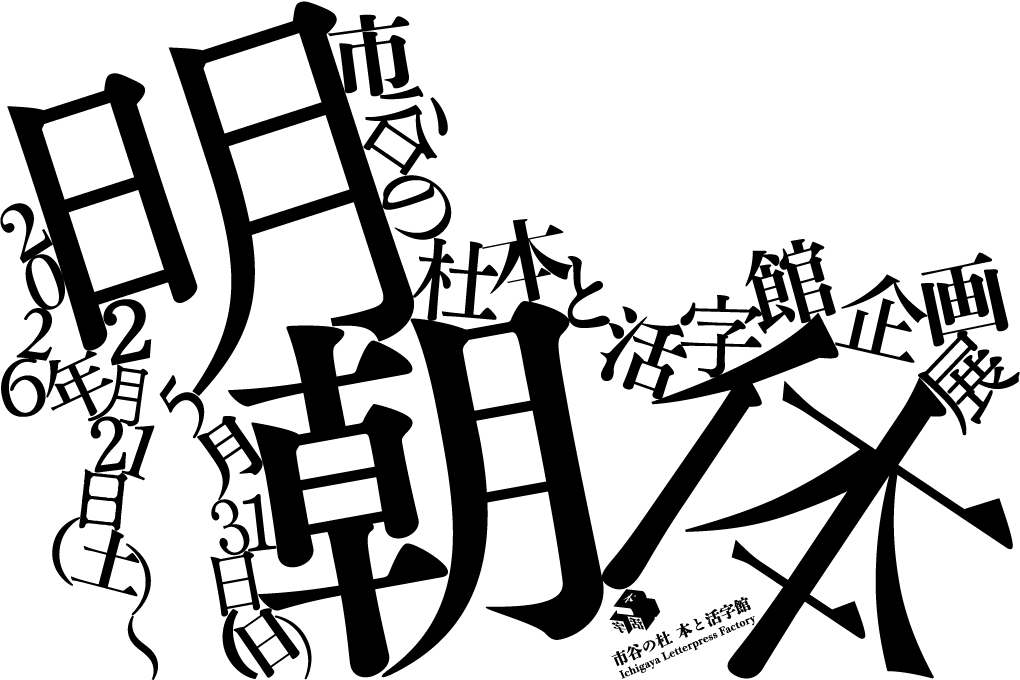
Monotype、企画展「明朝体」への資料提供に関するお知らせ
DNP主催「明朝体」展にMonotype®が協力――歴史ある多様な明朝体が一堂に、書体文化の魅力を発信
米国 Monotype Imaging Inc.の日本法人である Monotype株式会社(本社:東京都港区、以下 Monotype)は、大日本印刷株式会社(本社:東京都新宿区、以下 DNP)が運営する文化施設「市谷の杜(いちがやのもり)本と活字館」(東京都新宿区)にて開催される企画展「明朝体」へ、ライブラリフォントの筑紫書体シリーズをはじめとする明朝体資料を提供いたしました。
本企画展は、書体のスタンダードのひとつとして日本文化を支え続けてきた明朝体に焦点を当て、1世紀半以上にわたる明朝体の歴史を時代をさかのぼりながら紹介いたします。Monotypeは、本企画の趣旨に賛同し、書体デザインディレクター 藤田重信が生み出した、当社の日本語ライブラリフォントを代表する明朝体「筑紫明朝」の開発当初の資料等を提供し、展示に協力いたします。これを通じて、文字文化の魅力発信とフォント業界のさらなる発展に貢献してまいります。
筑紫書体とは
Monotype 書体デザインディレクター 藤田重信が2004年に生み出した「筑紫明朝」から始まった書体シリーズです。
金属活字の滲みを再現しながら新しさを取り入れ、画一的ではなく、文字本来の形をいかした字形デザインが特長です。懐かしさやあたたかみを感じさせ、見る人に郷愁を呼び起こします。一文字ごとの美しさはもちろん、文字組みした際の調和や文字同士が呼吸するような美しさも魅力です。明朝体、ゴシック体など、現在全15シリーズを展開しており、当社を代表する日本語ライブラリフォントの1つです。